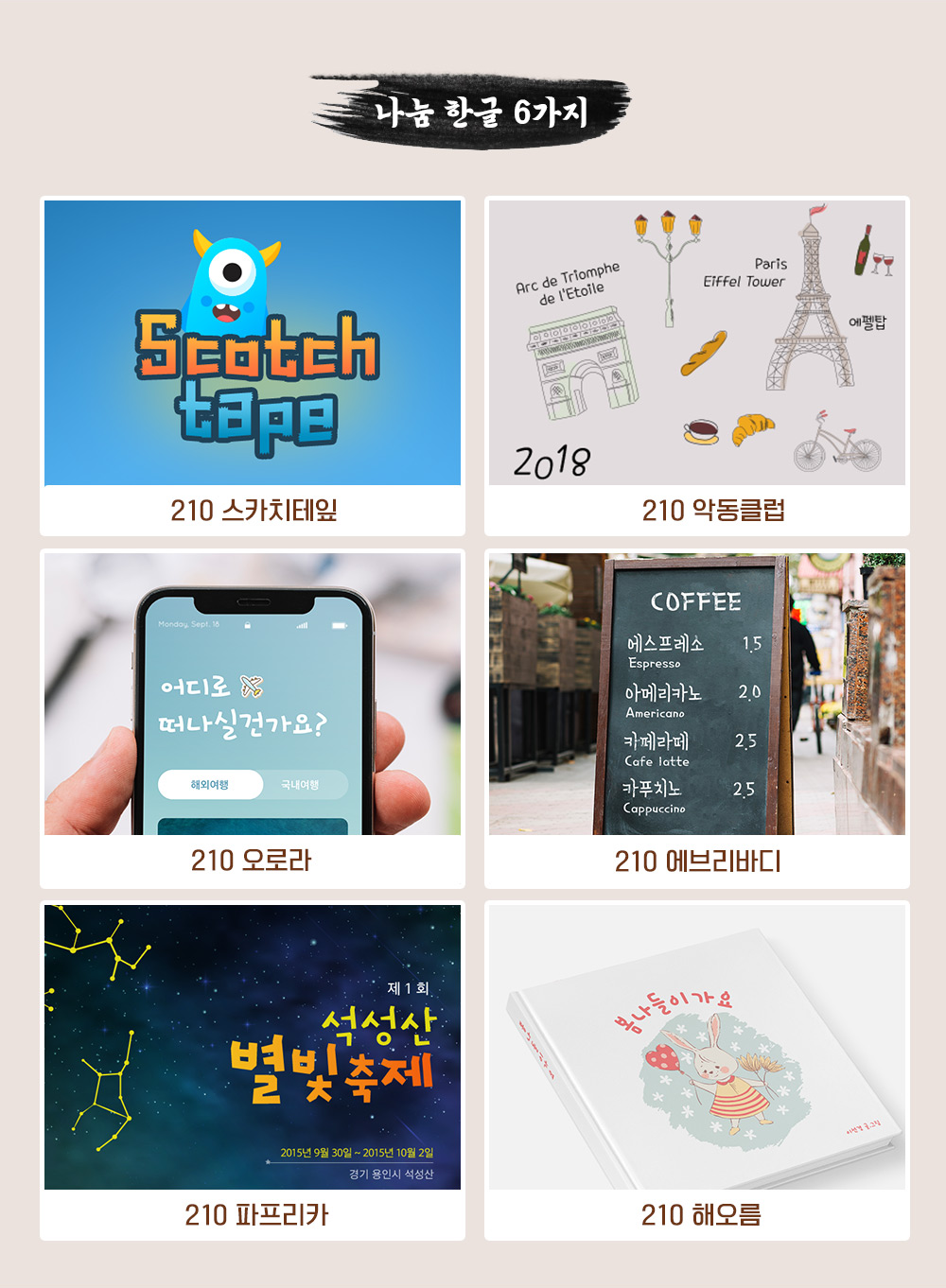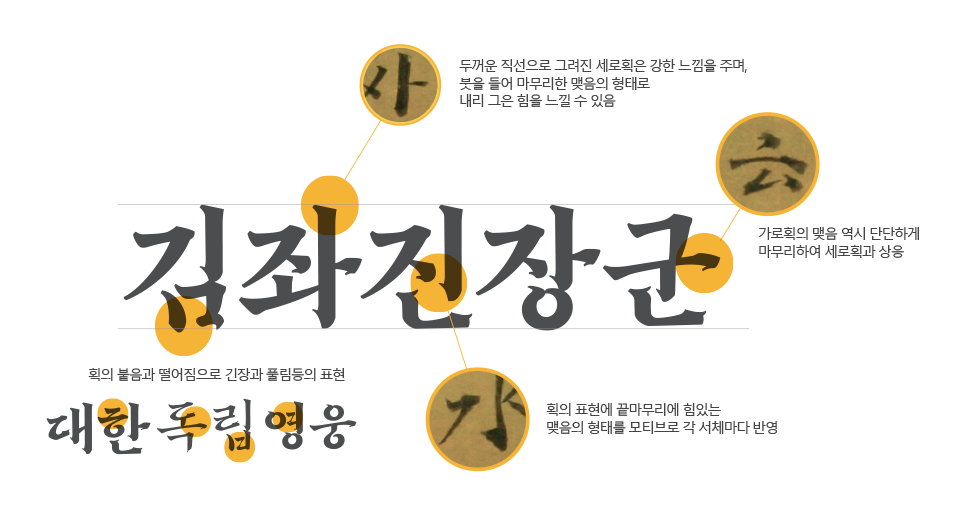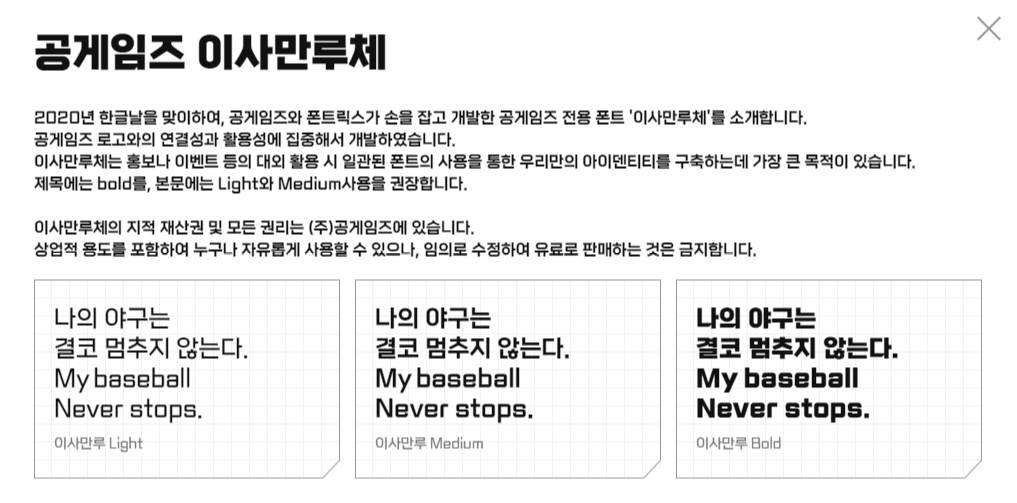
2020년 10월 9일, 574돌 한글날을 기념하여 많은 기업과 단체에서 기념 폰트를 제작하여 무료배포 하였습니다.
올해는 어떤 폰트들이 제작되어 배포되었는지 조금 늦었지만 살펴보고자 합니다.
네이버 ‘마루부리’
전년도에 손글씨 109종을 선보인데 이어 올해 네이버에서는 ‘마루 프로젝트’를 통해 ‘부리 글꼴’ 시험판을 지난 10월 7일 배포했습니다.
우리가 흔히 알고 있는 명조체는 중국 명조 시대 글꼴을 칭하는 것으로 우리 한글꼴에는 어울리지 않아 한글의 모음 끝에 새의 부리(beak)와 같은 모양이 있다는 뜻에서 ‘부리 글꼴’ 이라 이름을 지어 글꼴을 제작하고 있다고 합니다.
‘마루’는 순우리말 표현으로 ‘첫째, 기준, 맏이, 으뜸, 높은’ 이라는 의미를 가지고 있다고 합니다.
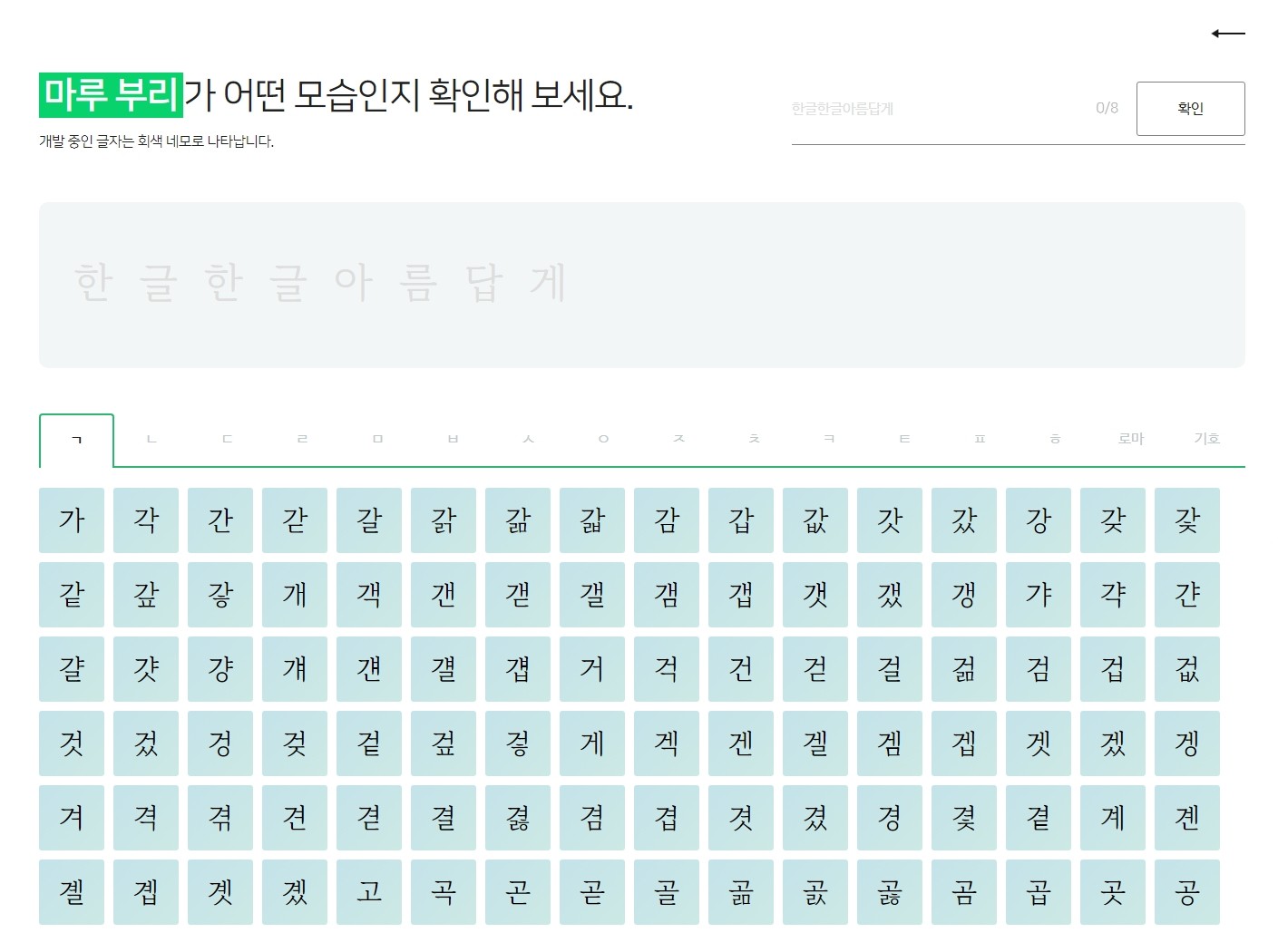
현재 ‘마루 프로젝트’는 완성형이 아닌 시험판으로 사용자들의 의견을 취합하여 계속 개선을 진행하고 있습니다.
10월 7일 공개 후 10월 21일까지 사용자의 의견을 취합하여 2021년 5종(Bold, Semi Bold, Regular, Light, Extra Light)의 최종 글꼴에 반영하여 출시한다고 합니다.
디자인210 ‘나눔 한글 6종’
디자인210에서 한글날을 맞아 무료폰트패키지를 ‘0원’에 판매하고 있습니다.
패키지에 포함된 폰트는 ‘210파프리카, 210해오름, 210스카치테잎, 210악동클럽, 210오로라, 210에브리바디’ 6종입니다.
배달의민족 ‘을지로10년후체’
전년도(2019년)에 배포한 을지로체의 10년 후 모습을 상상하여 만들어진 ‘을지로10년후체’입니다.
10년 동안 시간이 지나며 쌓인 햇빛과 비바람의 흔적을 느낄 수 있는 것이 특징입니다. 매년 독특하고 새로운 상상과 시도를 보여주는 배민인거 같습니다.
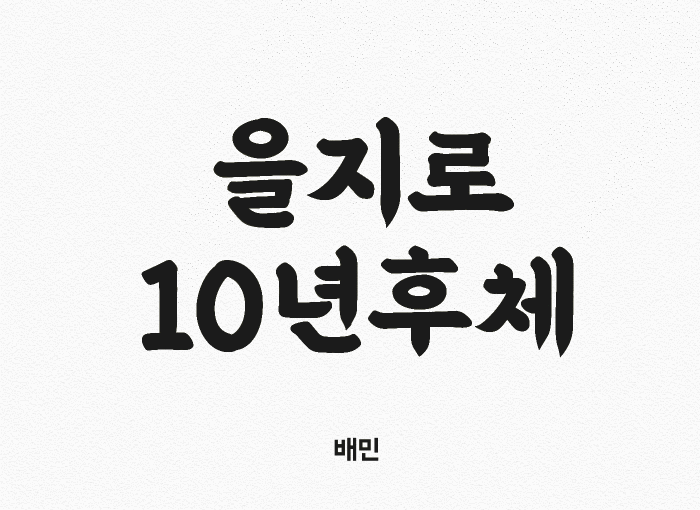
빙그레 ‘싸만코체’
2016년부터 매년 이어지고 있는 한글서체 시리즈 제 5탄, ‘빙그레 싸만코체’
자사 제품인 붕어싸만코의 특징을 잘 표현하고 있는 폰트, 달콤한 웃음을 머금은 붕어싸만코를 그대로 담아 제작되었다고 합니다.
한글 11,172자와 훈민정음 서문의 옛한글 31자, KS심볼 986자, 싸만코체를 더욱 재밌있게 즐길 수 있는 붕싸티콘 29자를 포함하고 있으며, Blod, Regular 2가지 타입이 제공됩니다.
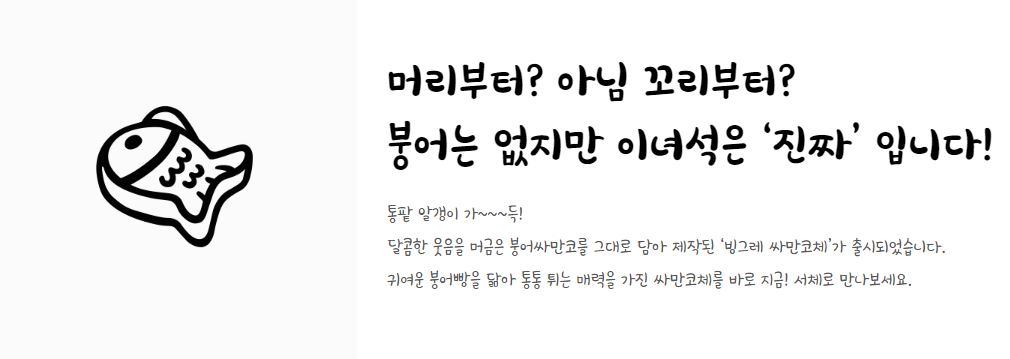
디자인210 뿌리깊은 프로젝트 9호 서체 ‘ON화룡도’
디자인210에서는 시대별 의미있는 글씨를 연구하며 뜻을 이어가고자 2018년 10월 석보상절을 시작으로 앞으로 출시되는 뿌리깊은 서체들이 3년간 개발, 런칭, 배포 됩니다.
이에 574동 한글날을 맞이하여 프로젝트 9호 서체인 ‘ON화룡도’가 공개되었습니다.
2019년 ‘ON정속언해’ 이후 6호 ‘ON송강가사’, 7호 ‘ON지장경언해’, 8호 ‘ON사략언해’, 그리고 9호 ‘ON화룡도’까지 발표되었고, 10호 ‘ON춘향전’은 2021년 1월 발표예정입니다.
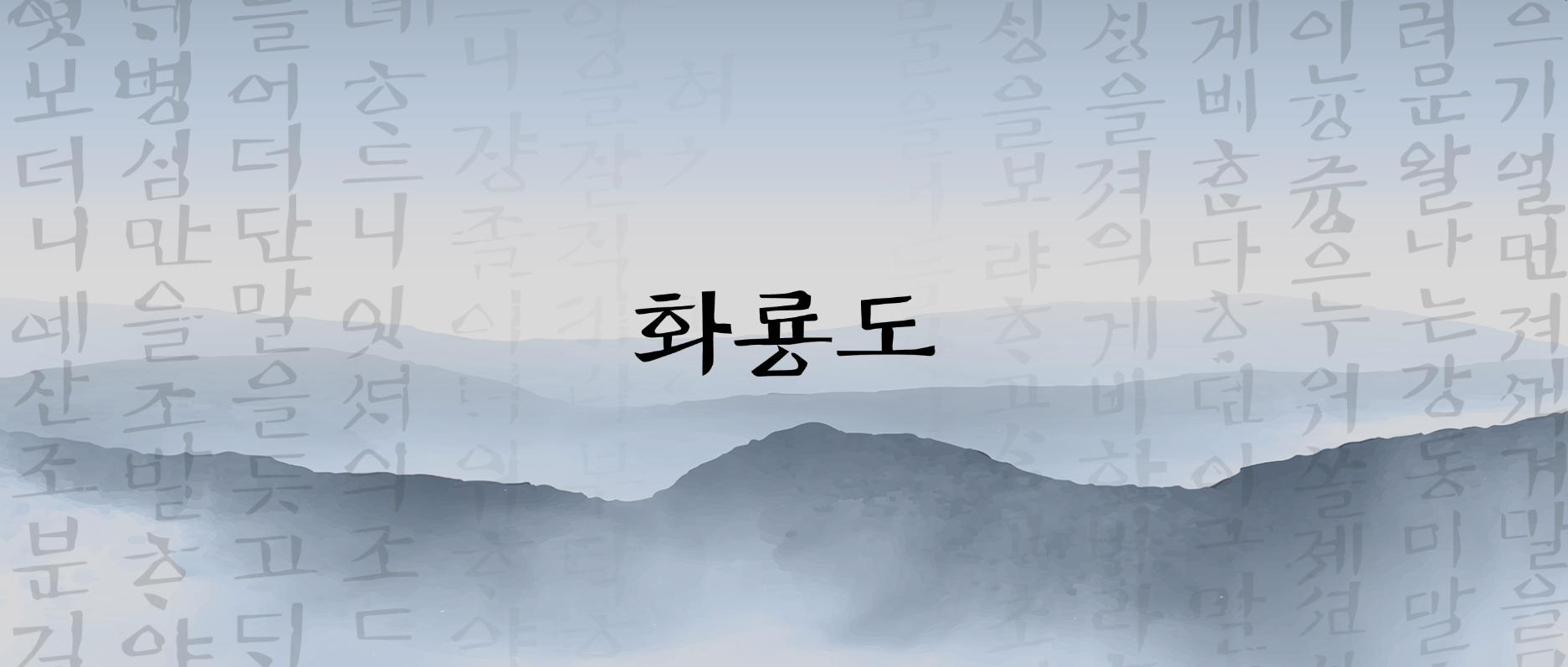
VITRO ‘비트로 코어, 비트로 프라이드’
스포츠 브랜드 비트로에서 한글날을 맞이하여 전용서체 2종을 제공했습니다.
비트로 전용서체는 힘세고 강한 고딕의 형태지만 모음에 부리가 있어 유니크한 스타일을 가졌습니다.
한글의 ‘ㅅ, ㅈ, ㅊ’등의 자소에서 시원하게 쭉 뻗은 획의 스타일과 각이 있는 ‘ㅇ’을 통해 스포츠의 힘과 역동성을 표현합니다.
또한 ‘ㅍ’에서 방향성 있는 유연한 움직임을 보여줍니다. 영문의 ‘p, u’등에서 각도가 있는 꺾임을 적용하여 한글과의 조화가 잘 이루어지도록 하였습니다.
숨어있는 재미 요소로 비트로 딩벳(Dingbat) 16종을 제공하여 소소한 즐거움을 주고 있습니다.
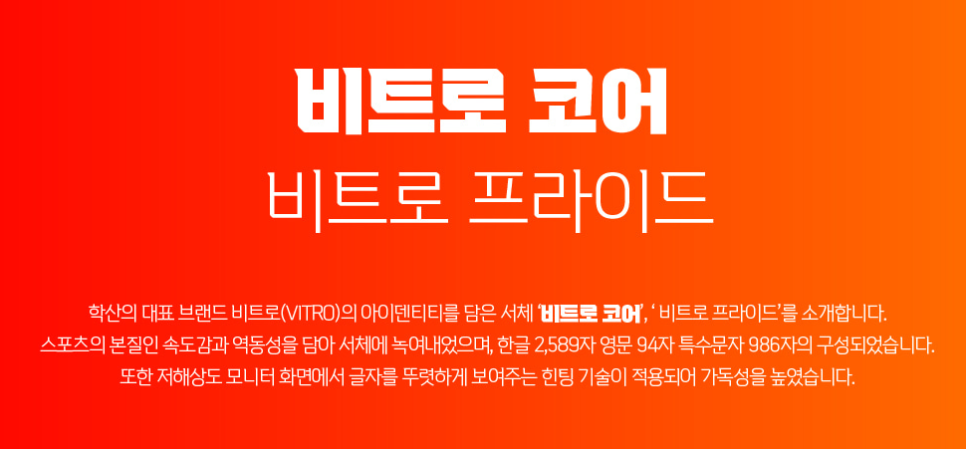
한글과컴퓨터 ‘한컴 훈민정음 세로쓰기체’
한글과컴퓨터에서 아래아한글 1.0을 시작으로 한글이 더 아름답게 쓰여질 수 있도록, 우리의 생각이 디지털세상에서 넓게 펼쳐질 수 있도록 한글 서체를 꾸준히 연구하고 배포하고 있습니다.
한글과컴퓨터 30주년을 맞이하여 한글의 다양한 매력을 담은 서체 3종(한컴 훈민정음 세로쓰기체, 한컴 말랑말랑체, 한컴 산스체)을 무료보 배포하였습니다.
전자책 플랫폼 서비스를 하고 있는 리디북스에서 전자책에서 잘 읽히는 글꼴을 찾는 독자들의 수고를 덜어드리고, 최상의 독서 경험을 제공하기 위해 만들었다고 합니다.
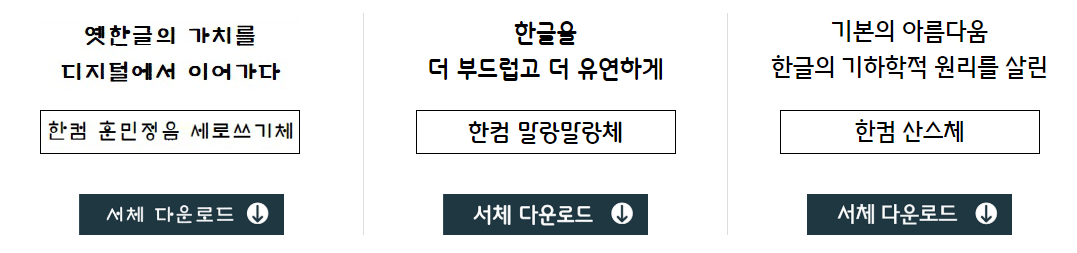
7-ELEVEN ‘김좌진장군체’
2020년 10월, 청산리전투 승전 100주년과 574돌 한글날을 맞아 업계 최초의 독립서체이자 국내 최초의 ‘김좌진장군체’를 선보였습니다.
김좌진 장군의 붓글씨에서 모티브를 얻어, 이를 한글의 구조에 맞게 정돈 후 활자화 하여 개발, 반흘림체의 디자인을 가미했으며, 강하게 내려 그은 세로획은 김좌진 장군의 강직하고 굳센 기세를 드러냅니다.
많은 기업과 단체에서 한글의 다양성과 우수성을 알리고 많은 사람들이 널리 이롭게 사용할 수 있는 서체를 개발하여 배포하고 있습니다.